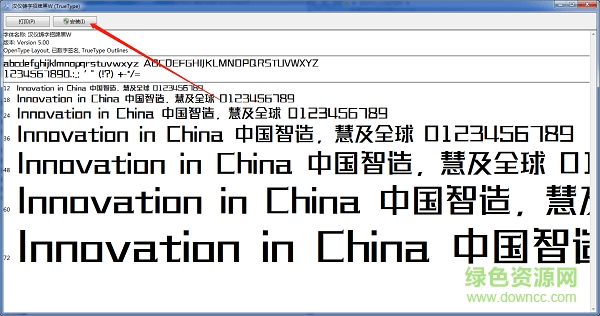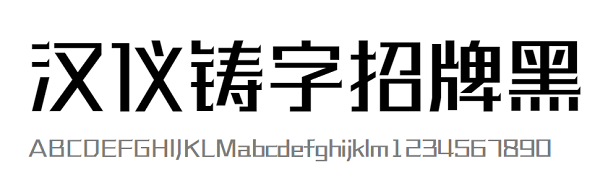
漢儀鑄字招牌黑W是漢儀鑄字系列的一款黑體字體,在鑄字系列里面,這算是比較有個性的一款了,看起來比較簡約,很現(xiàn)代化,文字依然沒有弧度,風(fēng)格也偏向力量,給人的視覺感就是硬度比較大,同時,重心較低,顯得非常穩(wěn)重,用來做宣傳字體的話,一定非常醒目!
1、推薦場景:標(biāo)志、導(dǎo)視、廣告、游戲、動漫、影視、包裝。
2、支持簡體中文、繁體中文、網(wǎng)絡(luò)常用中文簡繁、西文和數(shù)字。
3、字體風(fēng)格:簡約、現(xiàn)代、國際化、時尚、運動、男性、有力、穩(wěn)重、堅硬、帥氣、冰冷。